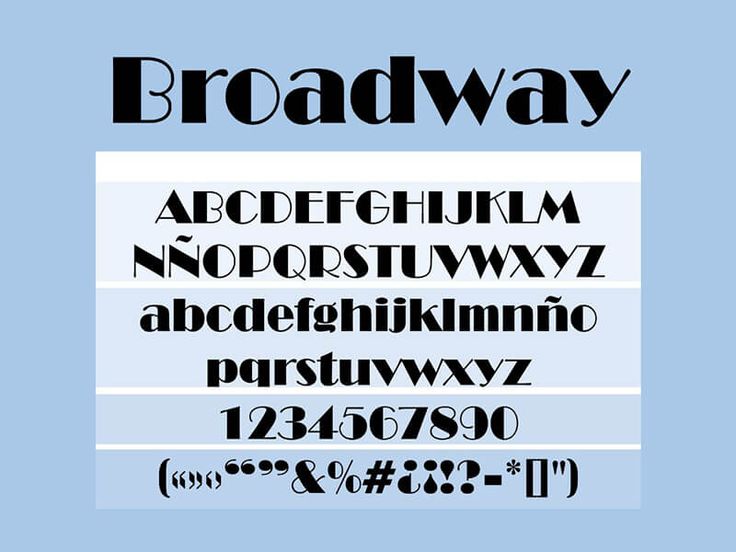
Font Broadway Việt hóa là bộ phông chữ thuộc dòng Art Deco Display kinh điển do Morris Fuller Benton thiết kế vào năm 1927, gắn liền với ánh đèn rực rỡ của các rạp hát nhạc kịch Broadway và kỷ nguyên Jazz hoa lệ của nước Mỹ. Với sự đối lập kịch tính giữa các khối nét cực dày và những đường thanh mảnh như sợi chỉ, font Broadway Việt hóa là chất liệu trực quan tuyệt vời để các kiến trúc sư, nhà thiết kế mang lại sự xa hoa cho các bản vẽ phối cảnh quán bar cocktail container, rạp chiếu phim mini hay biển hiệu homestay phong cách cổ điển thập niên 1920.
Hào quang nhạc kịch thập niên 1920 và độ tương phản kịch tính của font Broadway Việt hóa
Điểm cuốn hút của font Broadway Việt hóa nằm ở cấu trúc hình thể đậm chất tạo hình sân khấu: các thân chữ thẳng đứng dày đặc kết hợp cùng những đường cong hình học vát nhọn sắc sảo, tạo nên một trường thị giác đầy uy quyền và lôi cuốn. Sự chênh lệch độ dày nét đến mức cực đoan giúp các con chữ như đang tỏa sáng dưới ánh đèn rọi sân khấu, loại bỏ hoàn toàn sự tẻ nhạt của các kiểu chữ thương mại thông thường.
Sự ổn định về mặt cảm xúc của dòng font này tạo nên cảm giác lộng lẫy, tiệc tùng và tinh thần tự do của thời kỳ hoàng kim. Khi kết hợp cùng các vật liệu kiến trúc cổ điển như vách kính hoa văn hình học, inox mạ vàng gương, đá granite đen bóng hay đèn LED dây bóng tròn phong cách Marquee trong các căn nhà lắp ghép giải trí, Broadway tạo nên sự tương thích thẩm mỹ đầy ma lực.
| Phân loại phong cách | Art Deco Display / Theatrical Headline / High-contrast |
| Mục đích phù hợp | Biển hiệu rạp hát, logo quán bar, poster sự kiện |
Tư vấn từ chuyên viên: Broadway sở hữu độ tương phản nét cực đại và sức hút thị giác rất lớn. Để bản thiết kế đạt hiệu quả thẩm mỹ tốt, bạn chỉ nên sử dụng phông chữ này cho các tiêu đề chính, tên thương hiệu hoặc con số nổi bật.
03 Ứng dụng phông chữ Broadway vào công trình thực tế
Nhờ vẻ ngoài xa hoa và tính gợi hình sân khấu mạnh mẽ, bộ phông chữ này mang lại giá trị thực tế lớn trong khâu tạo điểm nhấn cho các công trình hiện đại:
- Biển hiệu mặt tiền phong cách Marquee cho Quán Bar Container: Những khối chữ dày của Broadway rất ăn ý khi gia công chữ nổi bằng kim loại sơn đen viền bóng đèn tròn LED vàng ấm, mang lại diện mạo rực rỡ như một nhà hát Broadway thực thụ giữa lòng phố.
- Hệ thống biển tên phòng và Bảng chỉ dẫn Lounge Nghỉ dưỡng: Phông chữ này khi gia công trên kính cường lực đen mạ chữ vàng gương sẽ giúp các căn phòng trong khu nhà lắp ghép toát lên phong thái quyền quý, tạo dấu ấn thị giác khó quên cho du khách.
- Bìa hồ sơ dự án kiến trúc giải trí và nghệ thuật biểu diễn: Sử dụng font Broadway Việt hóa cho tên dự án giúp tập hồ sơ trông như một ấn phẩm kỷ yếu danh giá, tạo niềm tin lớn với các chủ đầu tư yêu chuộng phong cách Art Deco hoa lệ.
03 Lưu ý bố cục font Broadway giữ trọn vẻ lộng lẫy và sắc nét
Để khai thác hiệu quả vẻ đẹp của dòng font đậm chất kịch nghệ này mà không gây cảm giác chật chội cho bản vẽ, người thiết kế nên lưu tâm một số kinh nghiệm sau:
- Tránh sử dụng ở kích thước quá nhỏ: Do có các nét thanh mỏng manh đối lập với thân chữ dày đặc, Broadway hiển thị đẹp nhất ở kích thước chữ từ 20pt trở lên trong in ấn. Ở kích thước quá nhỏ, các nét thanh có thể bị nuốt chửng bởi thớ giấy in hoặc cự ly quan sát.
- Bố trí khoảng thở rộng rãi: Bạn nên chừa khoảng trống thoáng đãng xung quanh tiêu đề để các khối chữ hình học có không gian lan tỏa hào quang, tránh để các chi tiết đồ họa phụ trợ chèn ép câu chữ.
- Kết hợp cùng gam màu vàng kim và đen tuyền: Broadway phát huy hiệu quả thị giác cao khi phối cùng các cặp màu kinh điển của thời kỳ Art Deco như vàng đồng ánh kim – đen bóng, đỏ nhung – vàng cát, làm nổi bật đường nét sắc sảo của bộ chữ.